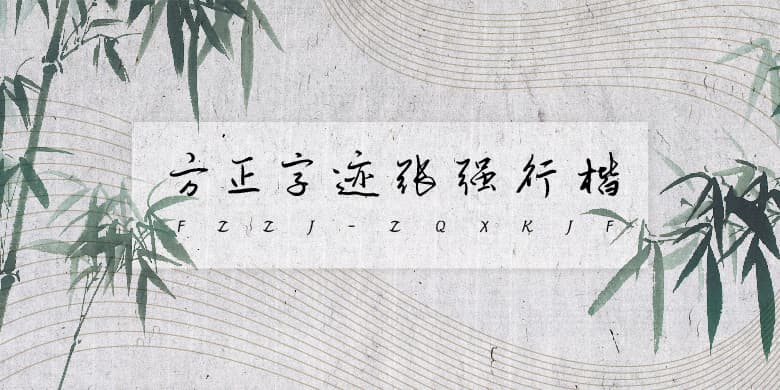
品牌:方正字迹设计师:张富强发行时间:2021字库编码:简繁扩展(GBK)、大陆简体(GB2312-80)分类:常规书写·毛笔字体属性:精品字
该款字结合了传统毛笔软笔和现代硬笔的写法和特点,使其既有毛笔的圆润厚重,又有现代硬笔的骨感和洒脱,线条比硬笔粗,比毛笔细,保留了传统的元素,同时又规避了纯硬笔的杂乱,这样不会显得太呆板。